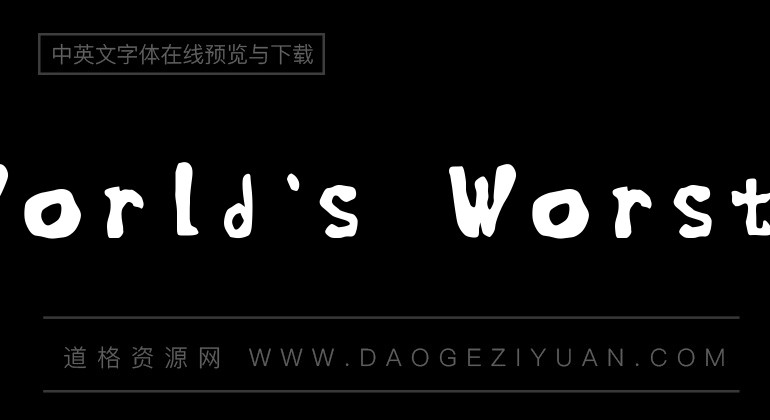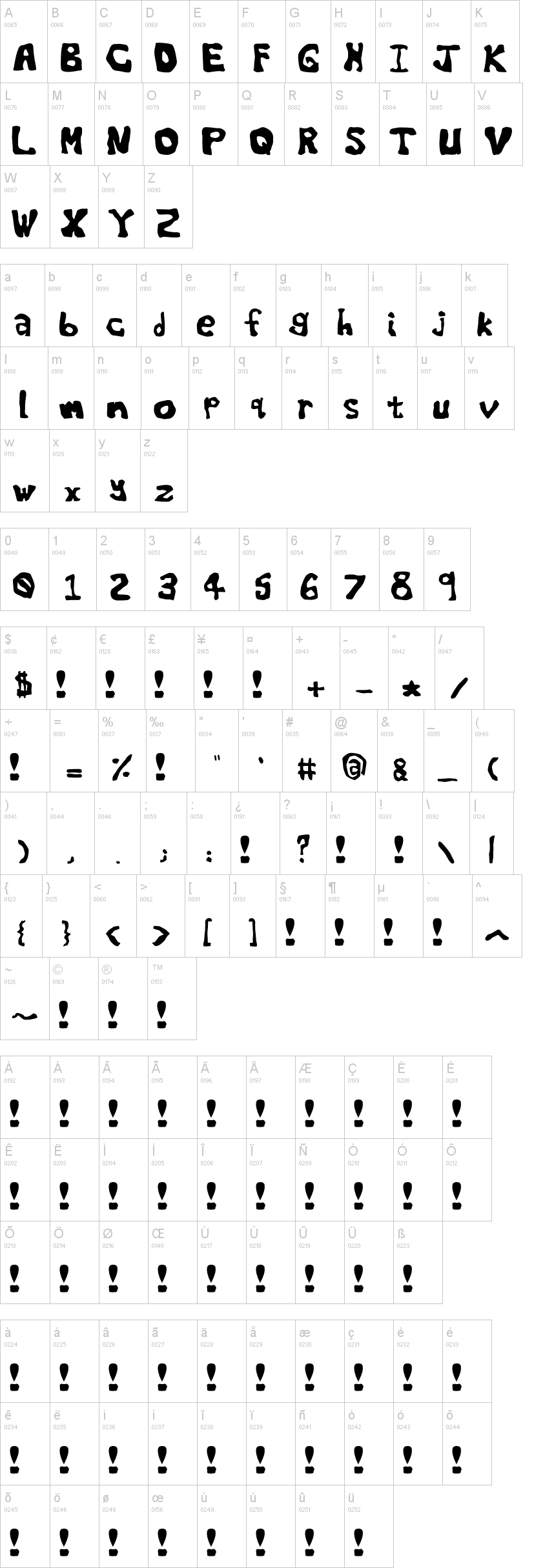
The World's Worst Font 是一款由英国设计师Simon Walker设计的字体,它是一种极其极端的拉丁文字体,其特点是字符形状简单、外观极其粗糙。它的字符结构极其简单,没有任何内在的艺术美感,甚至没有任何设计感,只是一种单调的、极其粗糙的拉丁文字体。由于它的极其粗糙的外观,它通常被用于娱乐或艺术目的,而不是用于正式的文档。内容介绍
The World's Worst Font是一款非常不错的手写艺术字体,具有很好的视觉感,适合于文化类的宣传设计、商业类品牌的广告和产品包装设计以及个性化文字排版等较多场景。